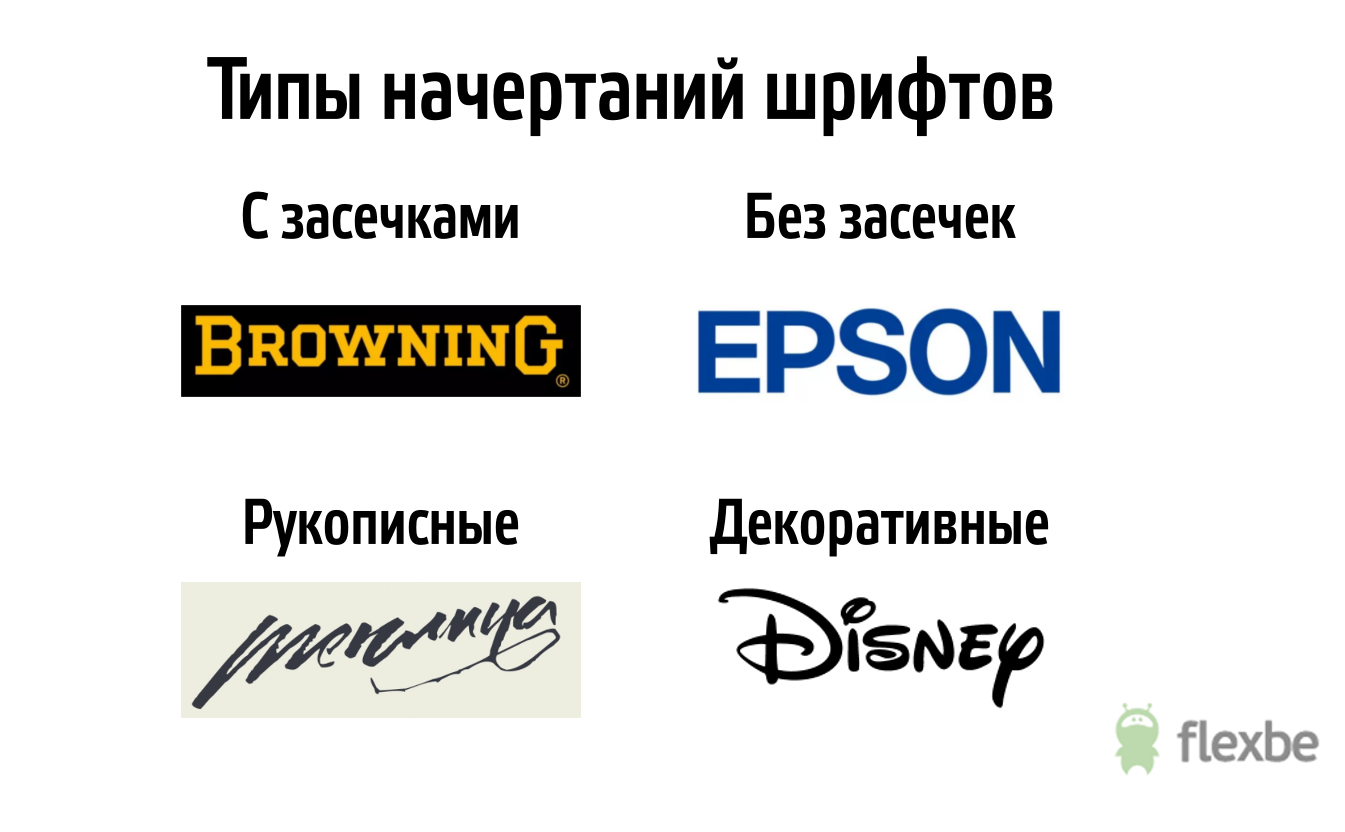
Какой шрифт выбрать для своего сайта – вопрос кажется простым, но только на первый взгляд. Как известно, в дизайне мелочей не бывает. И то, что сначала кажется не особо важным, в дальнейшем может сыграть важную роль.
1. Заголовки и текст
Для сайта оптимально выбрать два шрифта – один для заголовков, другой для текста. Это удобно для пользователей, им будет сразу ясно, где заголовок, а где текст. И дизайн самого сайта будет выглядеть более целостно.
Если двух шрифтов для выполнения нужных задач не хватает, и нужно использовать больше, то тогда придерживайтесь правила: не больше четырех шрифтов на странице.
Пример: заголовки – Verdana, текст – Arial.
2. С засечками или без?
Обычно шрифты с засечками (короткими штрихами на концах букв; так называемые serif-шрифты: Times New Roman, Garamond, Georgia) используются в печати. На бумаге такие шрифты воспринимаются хорошо, при чтении глаза устают меньше.
Следовательно, для веба обычно используются шрифты без засечек (так называемые sans-serif: Arial, Verdana, Trebuchet, Helvetica), потому что на экране, в отличие от бумаги, засечки превращаются в помехи, которые только усложняют восприятие текста. При этом важно оставлять нормальное межстрочное расстояние, чтобы глаз визуально мог отделять одну строчку от другой.
Считается, что любые правила можно нарушать, так что шрифты с засечками на сайте использовать можно… но очень-очень аккуратно и в исключительных случаях. Например, шрифтом с засечками можно набрать заголовок, чтобы сделать его еще более отличающимся от основного текста.
Кстати, есть еще шрифты monospace (Courier, Lucida Console, Monaco). Они похожи на шрифты для пишущей машинки, а сейчас используются для оформления кода.
3. Сочетание цветов
В отношении шрифтов действует такое же правило, как и в отношении общей цветовой гаммы сайта — используйте цветовой круг, и будет вам счастье. Например, удачные сочетания можно поискать в Color wheel от компании Adobe.
Естественно, тестируйте сочетаемость цветов не только между собой, но и на сайте, на том фоне, который вы выбрали. Особенно если фон не однотонный.
4. Выделение
Выделять текст можно не только цветом, но и выделением (текст — белый, выделение черным). Важно обратить внимание на контрастность — чем она выше, тем проще прочитать текст. Поэтому так легко воспринимать черные буквы на белом фоне и так сложно читать текст темно-серого цвета на светло-сером фоне.
5. Размер
Размер шрифта должен позволять без труда читать его.
В идеале это 12-14 пунктов; минимально — 10, максимально — 16.
Источники шрифтов
Google Fonts
Один из самых известных сборников бесплатных шрифтов. Присутствует латиница, кириллица и другие популярные и не очень языки; всего 900 семейств. Есть несколько фильтров — например, можно отсортировать шрифты по толщине букв, наклону или ширине.
Тексты можно редактировать, так что сразу можно посмотреть, как будет выглядеть нужная фраза в этом шрифте.
FontSpace
Здесь представлено больше 37 тысяч бесплатных шрифтов. Есть даже с пиктограммами (например, шрифт Trees Go с деревьями). Шрифты распространяются под разными лицензиями; некоторые нужно купить для того, чтобы использовать в коммерческих целях.
1001 Free Fonts
Еще один сайт с бесплатными шрифтами. Шрифты разделены на категории: например, в категории “Famous” (знаменитое) можно найти шрифты из «Парка Юрского периода» или «Черепашек-ниндзя».
FontStruct
Ресурс для тех, кто хочет создать шрифт самостоятельно. Если такого желания нет, то можно заглянуть в галерею, где есть созданные другими пользователями шрифты.
Font Squirrel
Еще один сайт со множеством разных шрифтов. Помимо бесплатного раздела, в нем есть раздел с платными шрифтами (Almost Free Fonts), где продаются шрифты с очень хорошей скидкой.
DaFont
Здесь можно найти бесплатные шрифты для личного и коммерческого использования. Есть интересная категория шрифтов “Foreign look”, которые стилизованы под буквы из алфавитов разных стран: русские, арабские, азиатские и другие.
Urban Fonts
Здесь есть платные и бесплатные шрифты — вторые выделены в отдельный раздел “Free”.
Abstract Fonts
Еще одна коллекция с постоянно пополняющимися шрифтами.
А если ищете какие-нибудь оригинальные платные шрифты, посмотрите в MyFonts. Там довольно большая коллекция всевозможных шрифтов.